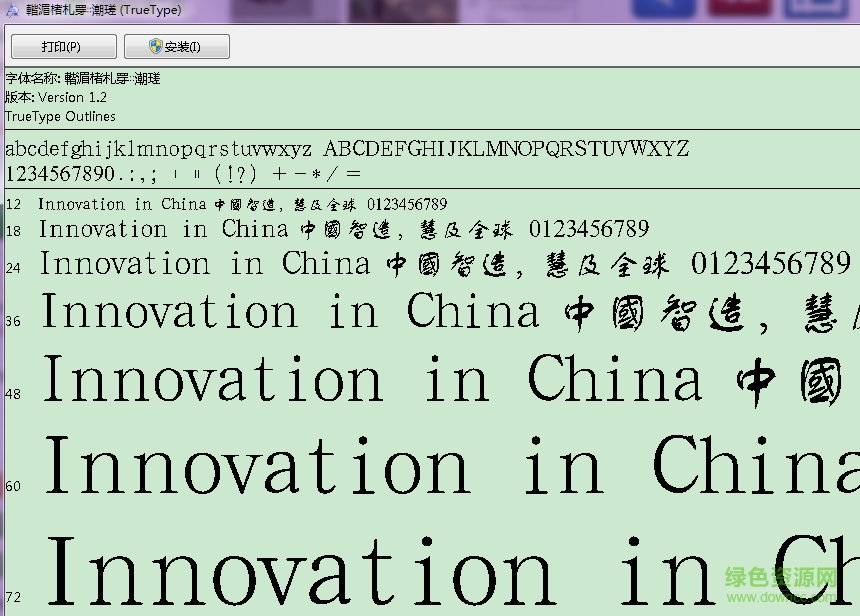
漢鼎繁舒體是一款非常正式的漢鼎字體,外觀中規(guī)中矩,喜歡的朋友趕緊來(lái)綠色資源網(wǎng)下載吧
十分不錯(cuò)好用的中文字體。創(chuàng)意設(shè)計(jì)方面用什么字體比較好呢?試試綠色先鋒小編推薦的這款漢鼎繁舒體官方版。漢鼎繁舒體字體筆畫流暢,字形整體瀟灑大方,以舒體字為原形而設(shè)計(jì),對(duì)其進(jìn)行了加工修飾,整體字形端莊大方,字庫(kù)完整